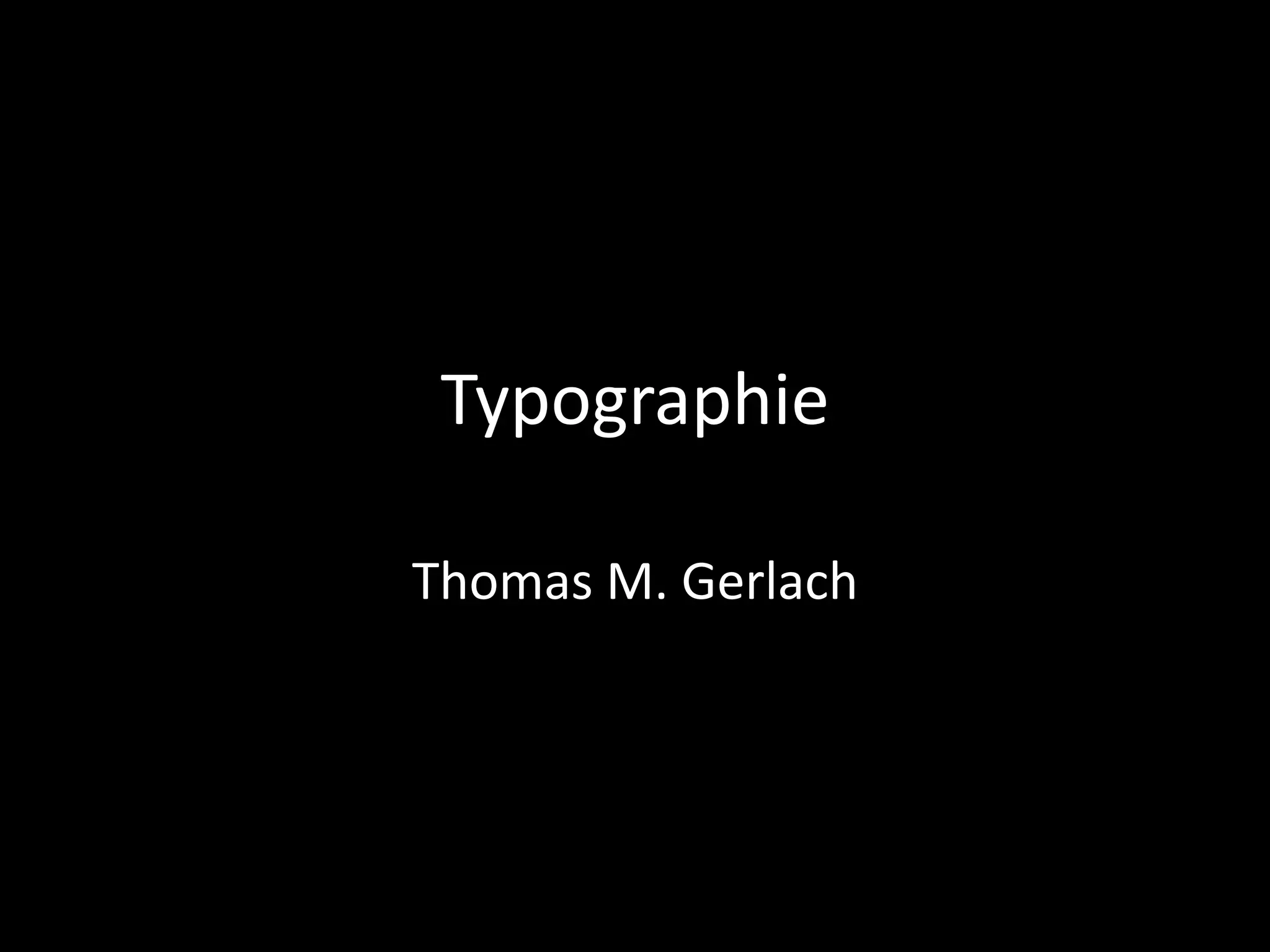
TypographieThomas M. Gerlach
T
Serifenschriften
Garamond:		ApfelkisteCaslon:					ApfelkisteBodoni:			ApfelkisteMinion Pro:			ApfelkisteDidot:			ApfelkistePalatino:		ApfelkisteTimes N. R.:		Apfelkiste
Serifenlose
Calibri:				ApfelkisteFranklin Gothic:		ApfelkisteFutura:				ApfelkisteGill Sans:			ApfelkisteHelvetica:			ApfelkisteArial:				Apfelkiste
Fixed
Courier New: 	ApfelkisteLetter Gothic:	Apfelkiste
Schmuckschriften
Chancery:				ApfelkisteBickham Script:						ApfelkisteChalkduster:	ApfelkisteCracked:					ApfelkisteLucida Blackletter:		ApfelkisteComic Sans:			Apfelkiste
Ausgezeichnet...
normal:				Apfelkistekursiv:			Apfelkistefett:		Apfelkistefett kursiv:Apfelkisteunterstrichen:	Apfelkistegesperrt:A p f e l k i s t eversal:				APFELKISTE
Wie läuft´s so?
SchrifttypeDas ist die ÜberschriftBislang unbekannte Täter stahlen am Sonntagvormittag Bargeld und Schmuck aus dem Wohnhaus eines landwirtschaftlichen Anwesens in Gonnersdorf (Ortsteil von Cadolzburg, Landkreis Fürth). Die Polizeiinspektion Zirndorf sucht Zeugen.Das ist die ÜberschriftBislang unbekannte Täter stahlen am Sonntagvormittag Bargeld und Schmuck aus dem Wohnhaus eines landwirtschaftlichen Anwesens in Gonnersdorf (Ortsteil von Cadolzburg, Landkreis Fürth). Die Polizeiinspektion Zirndorf sucht Zeugen.
AbsatzDas ist die ÜberschriftBislang unbekannte Täter stahlen am Sonntagvormittag Bargeld und Schmuck aus dem Wohnhaus eines landwirtschaftlichen Anwesens in Gonnersdorf (Ortsteil von Cadolzburg, Landkreis Fürth). Die Polizeiinspektion Zirndorf sucht Zeugen.Das ist die ÜberschriftBislang unbekannte Täter stahlen am Sonntagvormittag Bargeld und Schmuck aus dem Wohnhaus eines landwirtschaftlichen Anwesens in Gonnersdorf (Ortsteil von Cadolzburg, Landkreis Fürth). Die Polizeiinspektion Zirndorf sucht Zeugen.
Ligaturen
Flft in ArialFlft in Calibri
Unterschneidung
BodoniWochenende
Schriften richtig einsetzen
Fristlose Kündigung
Einladung ZumKindergeburtstag
Wilde Party!
Mit dem Wlanins INternet
CafeKranzler
Und zum Schluß...
Kein Word-Art!!!